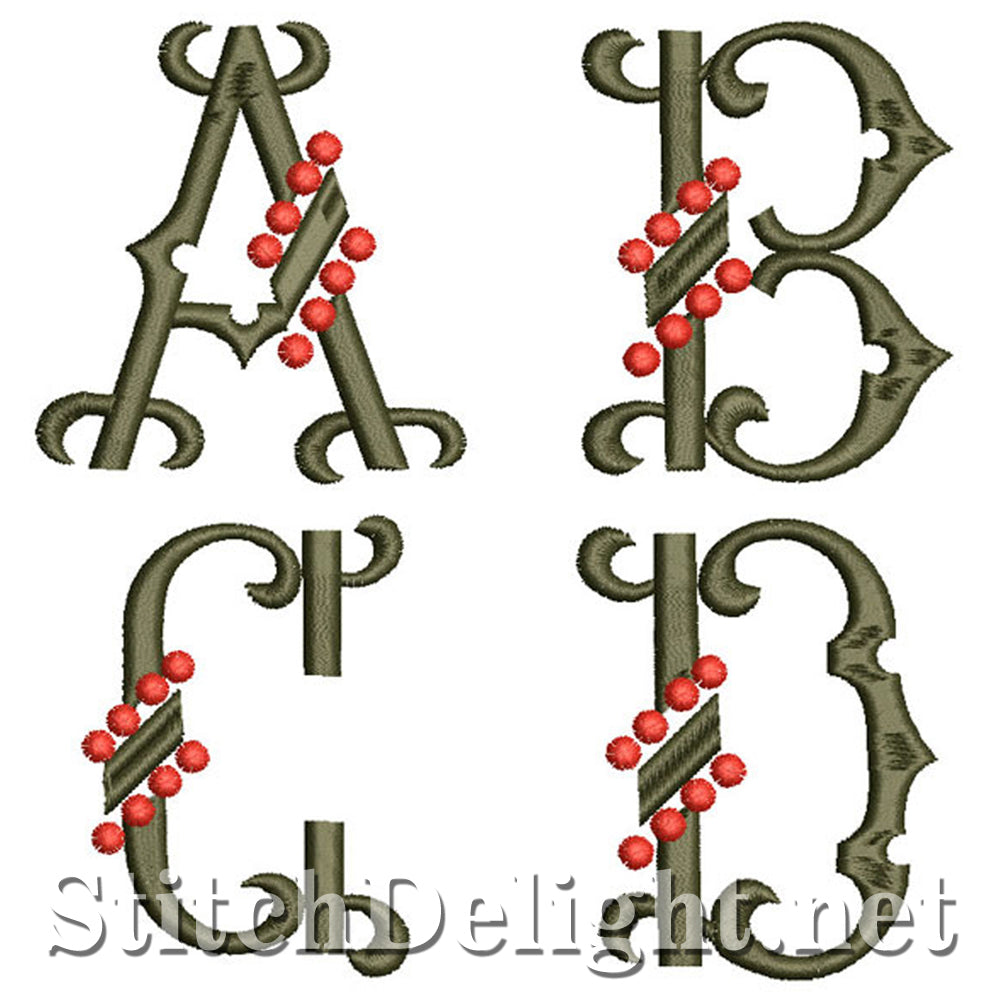
Police élégante avec une hauteur de lettre de 65 mm / 2,57" - un peu plus musclée que les autres polices, ce qui la rend parfaite pour les projets de fête des pères.